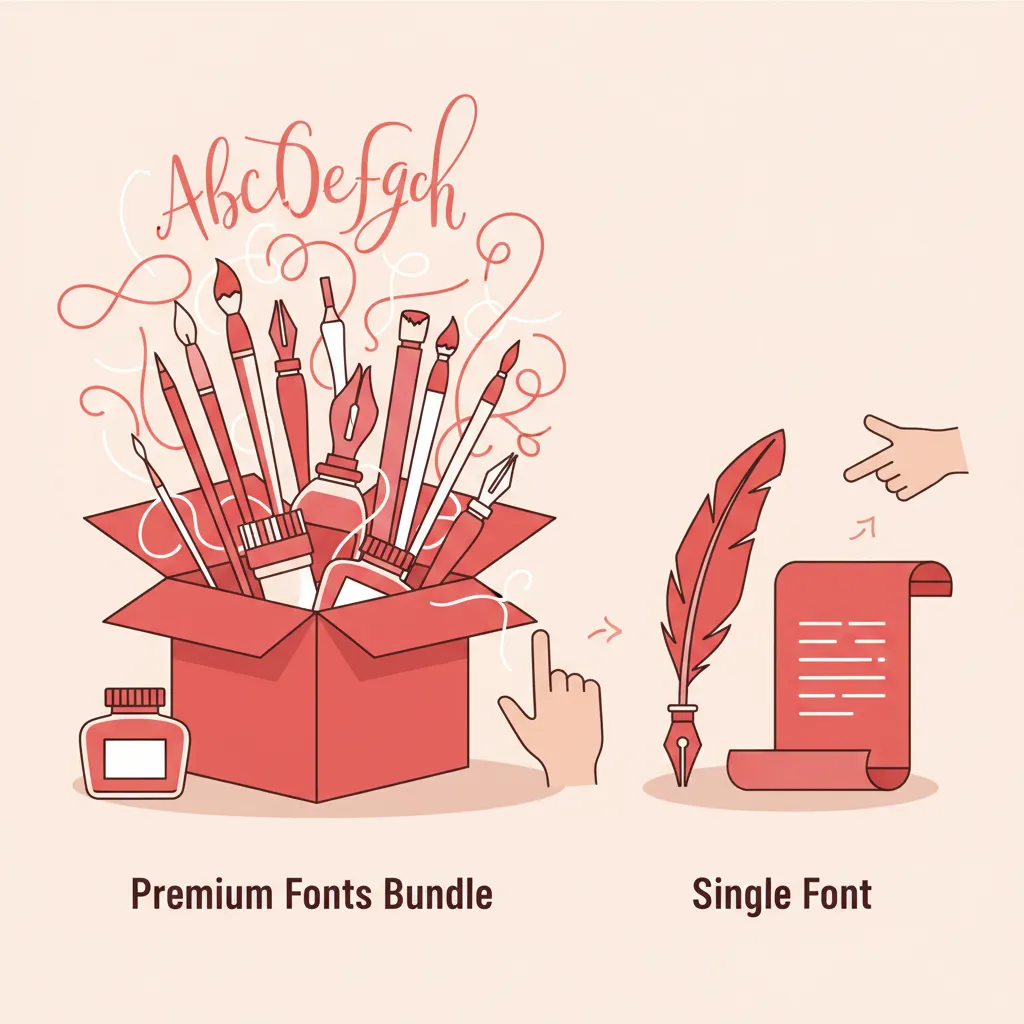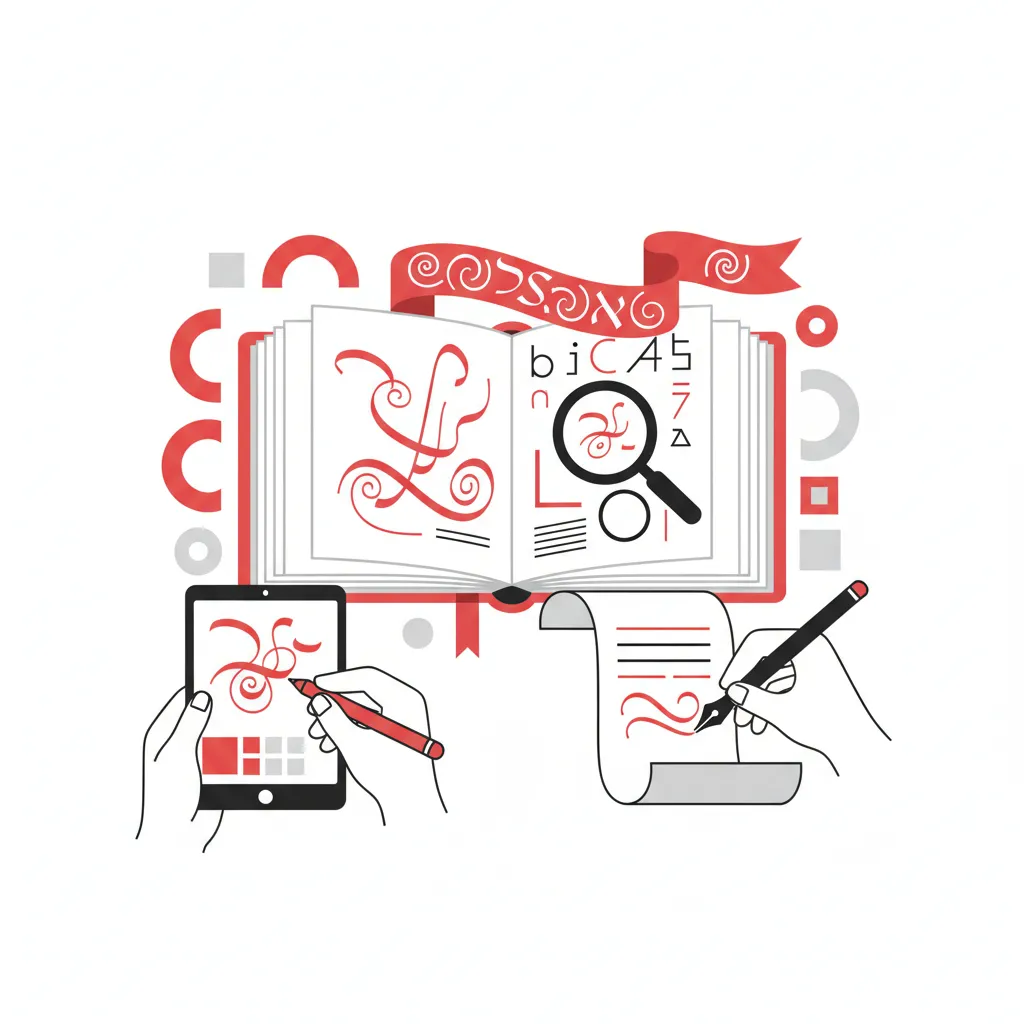
חבילת פונטים פרימיום – מה כדאי לבדוק לפני הרכישה
מעצב גרפי שרוכש חבילת פונטים פרימיום בלי לבדוק את תנאי הרישיון עלול למצוא את עצמו בבעיה משפטית – גם אם שילם על הפונטים כסף רב. זו לא תיאוריה; זו טעות נפוצה שמעצבים עושים כשהם מתמקדים רק במראה הפונט ולא בפרטים הטכניים שמאחוריו. לפני שמשקיעים בחבילת פונטים עברית, כדאי לדעת בדיוק מה לבדוק – ואיך להשוות בין האפשרויות הקיימות בשוק כדי לקבל את הערך הטוב ביותר לכסף.
חבילת פונטים פרימיום – מה חשוב לדעת לפני הרכישה:
• מספר המשקלים (Light, Regular, Bold) קובע את הגמישות העיצובית של החבילה.
מה ההבדל בין חבילת פונטים פרימיום לרכישת פונט בודד?
חבילת פונטים היא אוסף של מספר משפחות פונטים הנמכרות יחד במחיר אחד, בדרך כלל עם הנחה משמעותית לעומת רכישת כל פונט בנפרד. עבור מעצב שעובד על פרויקטים מגוונים – מיתוג, הדפסה, ווב ואפליקציות – חבילה כזו יכולה לחסוך סכומים משמעותיים לאורך זמן.
ההבדל המהותי הוא בגמישות. פונט בודד מתאים לפרויקט ספציפי; חבילה מאפשרת לעבוד עם מגוון אופי טיפוגרפי מבלי לחפש פתרונות חדשים לכל לקוח. לפי נתונים ממקורות בתחום, חבילות פונטים בעברית לשימוש מסחרי נחשבות לפתרון שחוסך למעצבים ולבוני אתרים אלפי שקלים בשנה.
עם זאת, לא כל חבילה שווה לחבילה אחרת. השאלה אינה רק "כמה פונטים מקבלים?" אלא "מה איכות הפונטים, מה הרישיון, ואיך הם מתנהגים בפועל?" – אלה השאלות שצריכות לכוון כל החלטת רכישה.
5 קריטריונים לבדיקה לפני הרכישה
כל קריטריון שמפורט כאן יכול להיות ההבדל בין חבילה שמשרתת אתכם שנים לבין השקעה שמתברר כאחר כך שהיא לא מתאימה לצרכים שלכם.
3. מספר המשקלים ומשפחות הפונטים [4]
גמישות עיצובית נמדדת לפי מספר המשקלים הזמינים. פונט עם משקל אחד בלבד מגביל מאוד את אפשרויות ההיררכיה הטיפוגרפית. חבילה איכותית תציע לפחות Regular, Bold ו-Light לכל משפחה, ובאופן אידיאלי גם משקלים ביניים.
לדוגמה, כשמחפשים פונט לטקסט רץ, חשוב שיהיו לפחות שלושה משקלים כדי ליצור ניגודיות בין כותרות לגוף הטקסט. פונט ככה התעוררתי, למשל, מציע חמישה משקלים שונים – קל, רגיל, בולד, כבד ומשפחה מלאה – מה שמעניק גמישות מרבית לפרויקטים מגוונים.
4. מגוון הסגנונות בחבילה [5]
חבילה טובה לא תכלול רק גרסאות שונות של אותו סגנון. היא תציע גיוון אמיתי: פונטים לכותרות לצד פונטים לטקסט רץ, סגנון קליגרפי לצד סגנון מודרני נקי, וסריף לצד סנס-סריף. ככה החבילה משרתת פרויקטים שונים מבלי לאלץ אתכם לרכוש תוספות.
5. תמיכה בניקוד ובאותיות מיוחדות
בעברית, תמיכה בניקוד היא קריטית לפרויקטים רבים – ספרים, חומרים חינוכיים, תפריטים, הזמנות. בדקו אם הפונטים בחבילה כוללים גלופות מנוקדות מלאות, ולא רק האות הבסיסית. בנוסף, פונטים שתומכים גם בלועזית (דו-לשוניים) מוסיפים ערך רב לפרויקטים שמשלבים שפות.
טבלת השוואה: מה לחפש בחבילה
הטבלה הבאה מסכמת את הקריטריונים המרכזיים ומה נחשב לסטנדרט בסיסי לעומת חבילה מקצועית:
קריטריון חבילה בסיסית חבילה פרימיום
רישיון דסקטופ בלבד דסקטופ, ווב, אפליקציה
פורמטים TTF בלבד OTF, TTF, WOFF, WOFF2
משקלים 1-2 משקלים 4+ משקלים למשפחה
ניקוד חלקי או ללא מלא
מגוון סגנונות סגנון אחד כותרות, גוף, קליגרפיה
שימוש מסחרי לא תמיד כלול
איך לבחון את איכות הטיפוגרפיה לפני שקונים?
מראה מושך בתצוגה המקדימה אינו ערובה לאיכות. יש מספר בדיקות פרקטיות שכדאי לבצע לפני כל רכישה של חבילה:
• בדיקת קריאות בגופים קטנים – הורידו דוגמת PDF אם זמינה, ובדקו איך הפונט נראה ב-10-12pt. פונט שנראה מצוין ב-72pt אך קשה לקריאה בגופים קטנים הוא בעיה אמיתית.
• בדיקת מרווחי אותיות – האם המרווחים (kerning) נראים טבעיים בטקסט רץ? בעברית, צמד האותיות ר-ו, מ-ה, ש-ל הם מבחן טוב.
• בדיקת עקביות בין משקלים – האם ה-Bold נראה כמו גרסה כבדה של ה-Regular, או שהם נראים כמו פונטים שונים לגמרי?
• בדיקת רנדור על מסכים שונים – אם הפונט מיועד לווב, בדקו דוגמאות על מסכים בצפיפות שונה (Retina לעומת מסכים רגילים).
ב-Google Fonts ניתן לראות כיצד פונטים מסוימים מתנהגים בסביבת ווב – זה יכול לשמש נקודת ייחוס להבנת מה מצפים מפונט איכותי. עם זאת, פונטים עבריים פרימיום מציעים עומק טיפוגרפי שפונטים חינמיים לא תמיד מגיעים אליו, כפי שמוסבר במאמר על התאמת פונטים.
רעיונות ליישום מיידי:
• צרו "ספריית בדיקה" – הכינו קובץ עיצוב עם אותו טקסט בגדלים שונים, ובדקו כל פונט שאתם שוקלים לרכוש על אותו תבנית.
עם הכלים האלה, הרכישה הבאה של חבילת פונטים תהיה מבוססת, מושכלת, ותשרת אתכם לאורך שנים רבות.